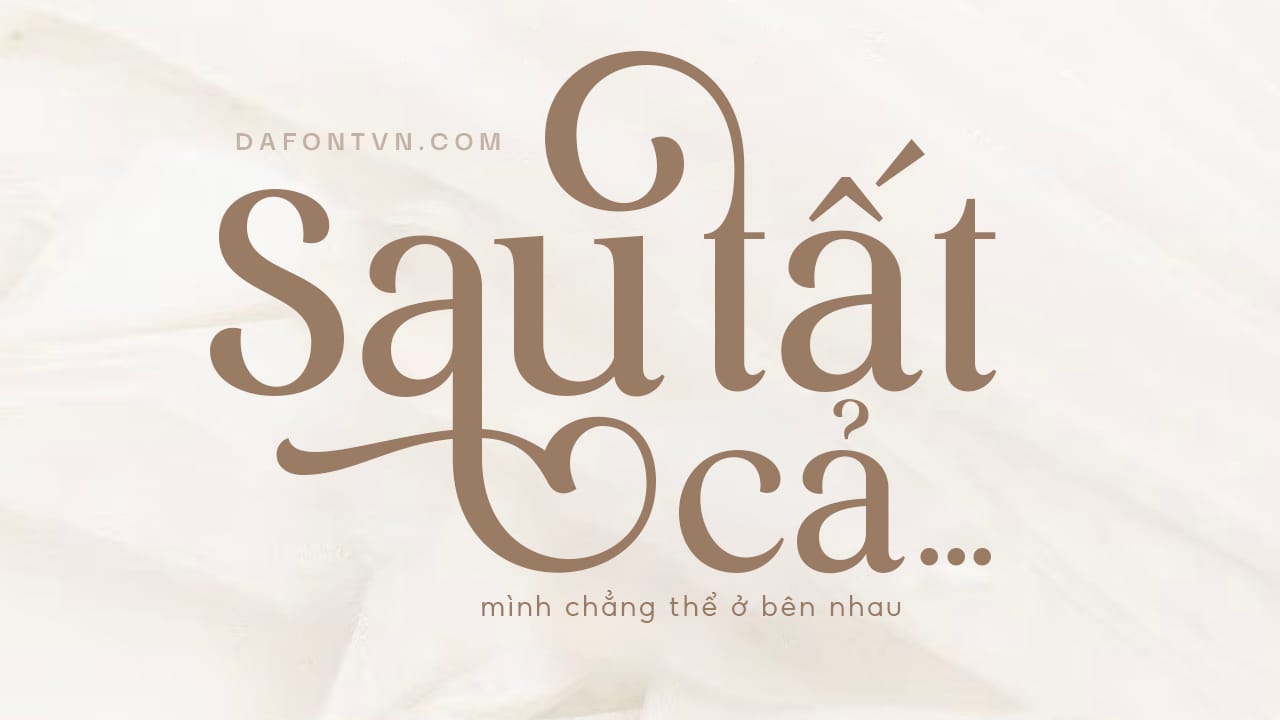
Font Salute Việt hóa mang phong cách cổ điển và hiện đại với các ký tự độc đáo và các ký tự thay thế tuyệt vời sẽ mang lại cho bạn những thiết kế cực kỳ ấn tượng. Với các nét chữ được thiết kế mềm mại đi kèm với nó là rất nhiều glyph uốn lượn tuyệt vời của các chữ thường càng tạo nên vẻ đẹp của font chữ này.
Font Salute phù hợp cho nhiều thiết kế khác nhau cần sự mới mẻ, tươi sáng, bắt mắt, mang phong cách đẹp cho các thiết kế như bìa sách, tạp chí, thiệp mời, typography…